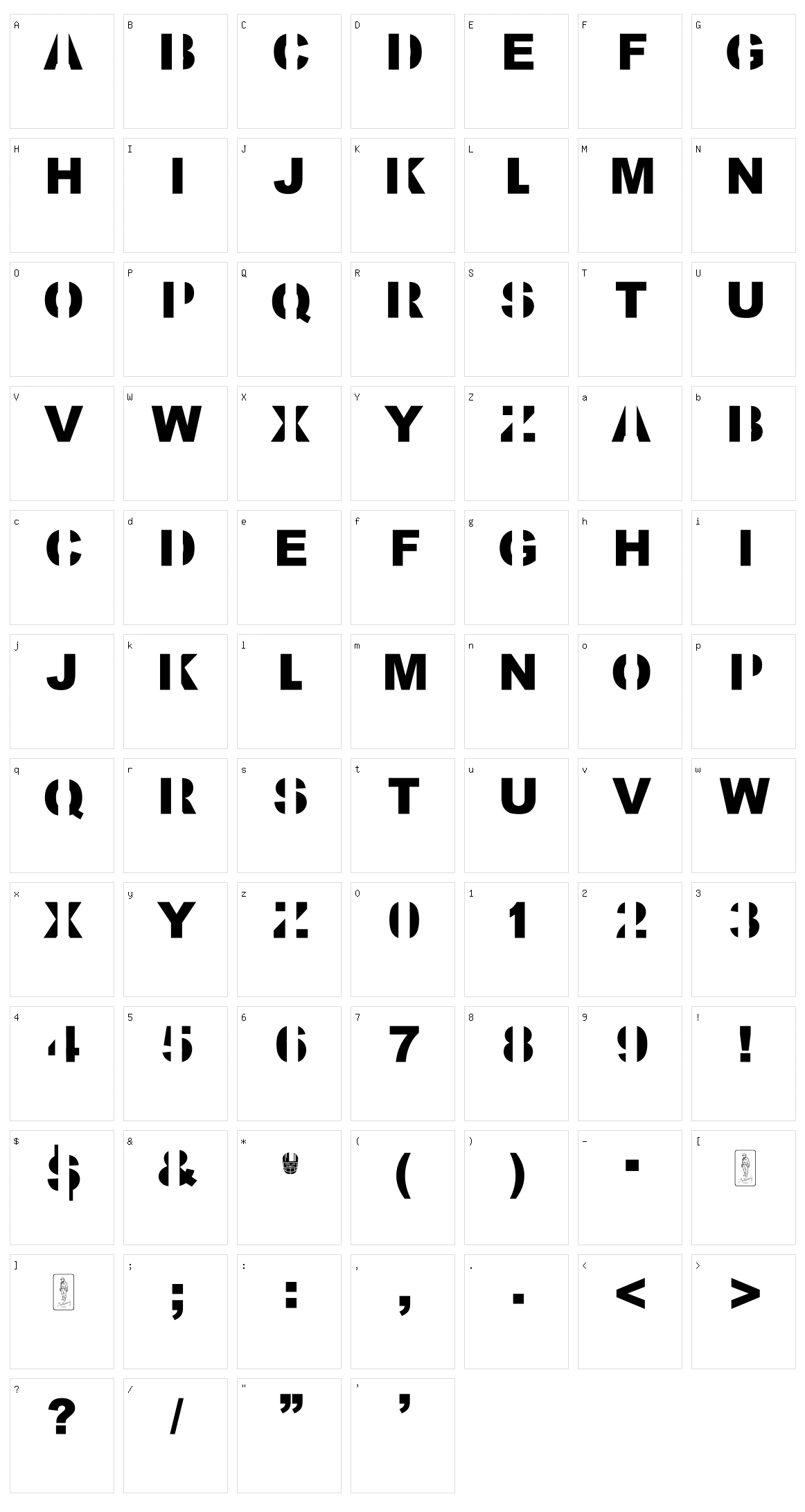
"Kill All Fonts" es una fuente gratuita de MatreroG
fuentes.
"Kill All Fonts" esta basada en la tipografía del
disco "Xtrmntr" de Primal Scream y en el simple "Kill
all hippies"